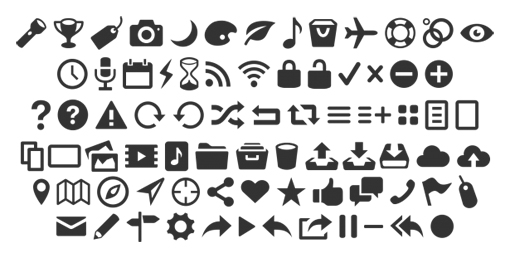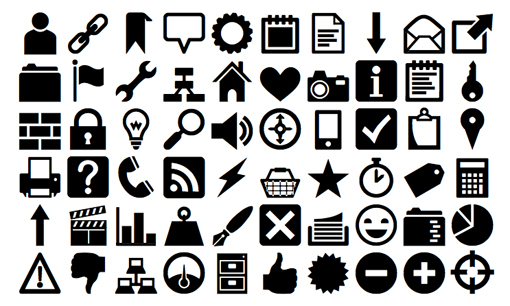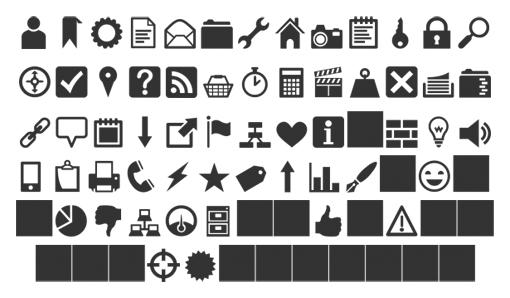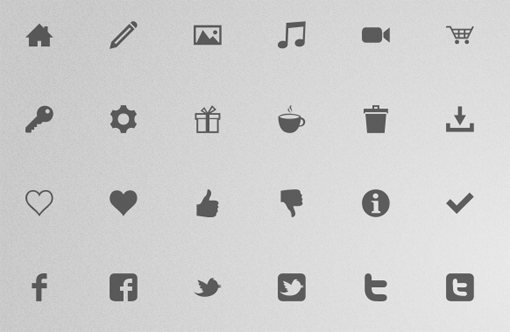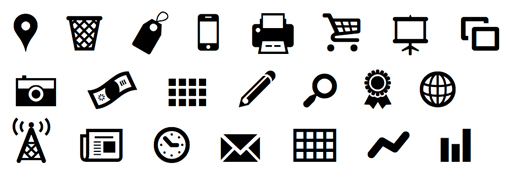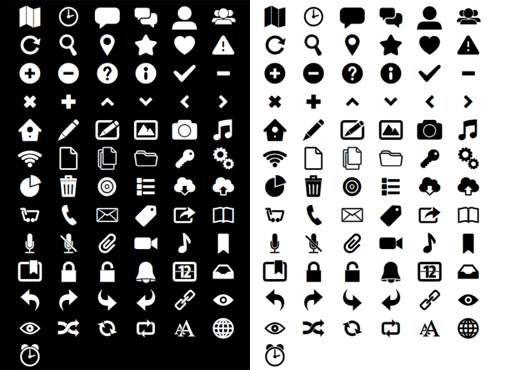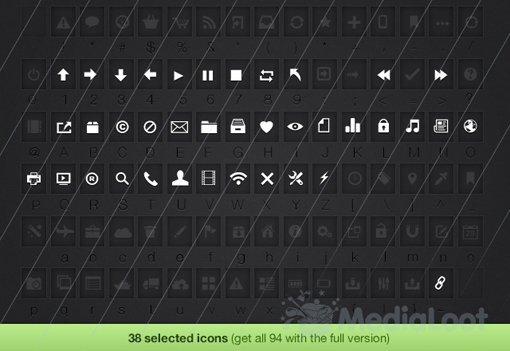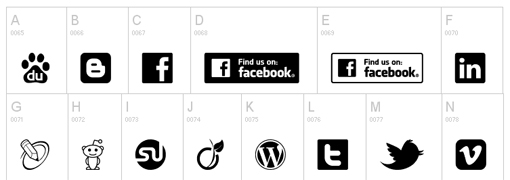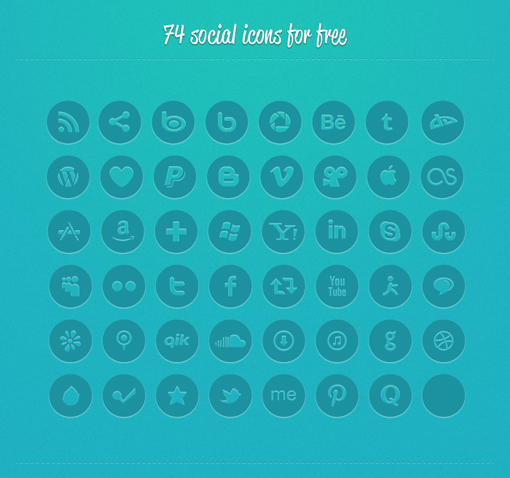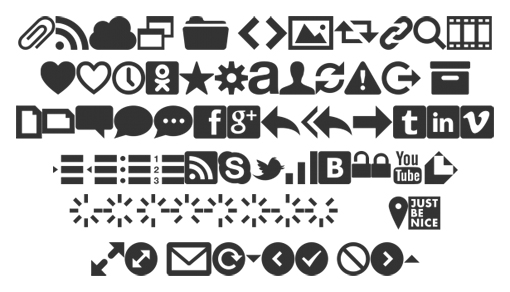
12 бесплатных шрифтов с символами
Представляем вашему вниманию подборку из двенадцати удивительных бесплатных шрифтов, у которых вместо букв—символы. Использование таких шрифтов—это невероятно универсальный способ создать интересную и  простую графику для сайта. Все эти шрифты вы можете скачать абсолютно бесплатно, для этого просто перейдите по ссылке.
Entypo
Signify Lite
Social Media Icons
Heydings
IcoMoon
Iconic Icon Set – 171 символ
Modern Pictograms
Heydings Common
Web Symbols typeface
PulsarJS @FontFace 73 Free IconFont | xperiments.es
Social Logos Font
Web Symbols